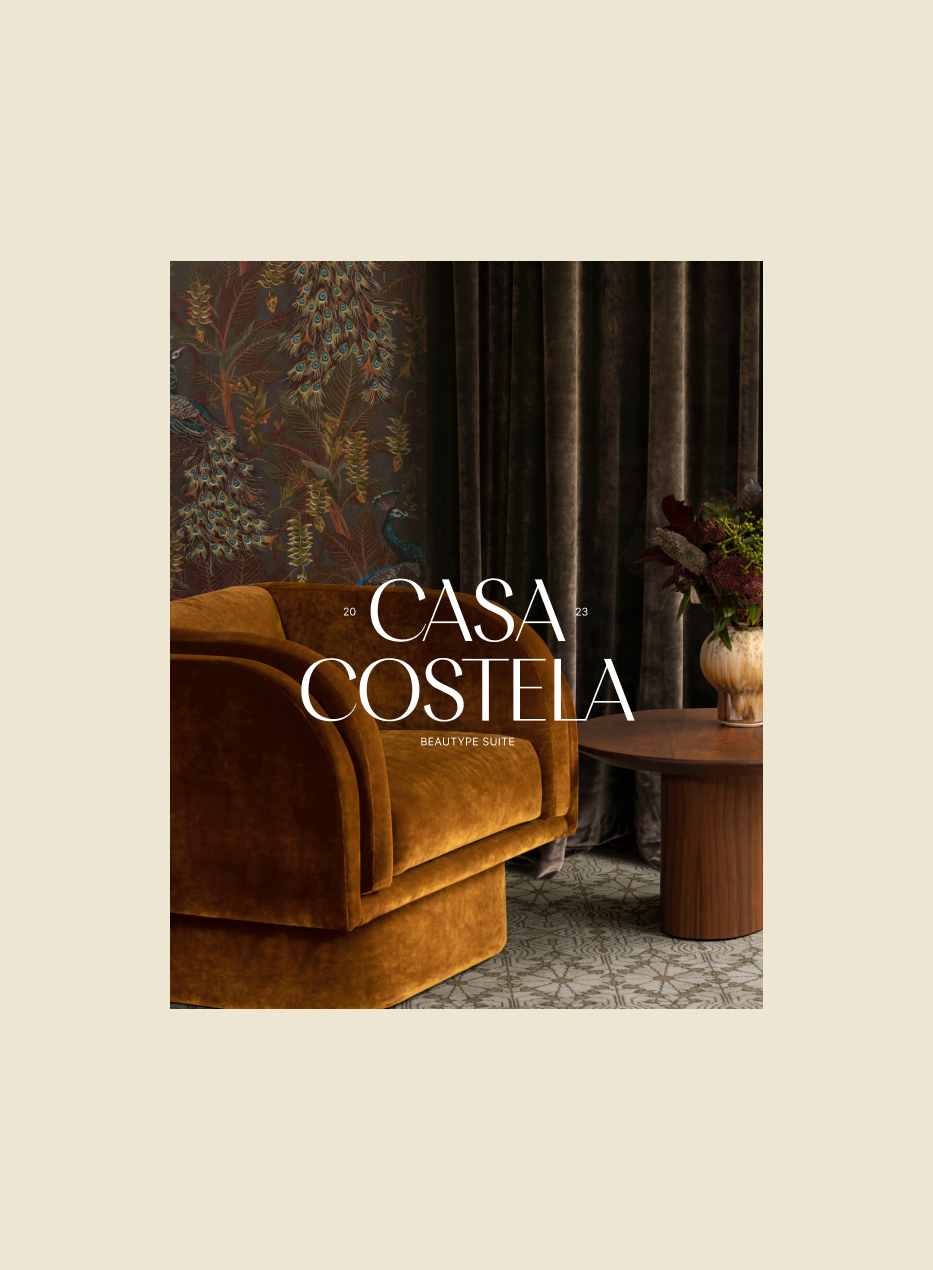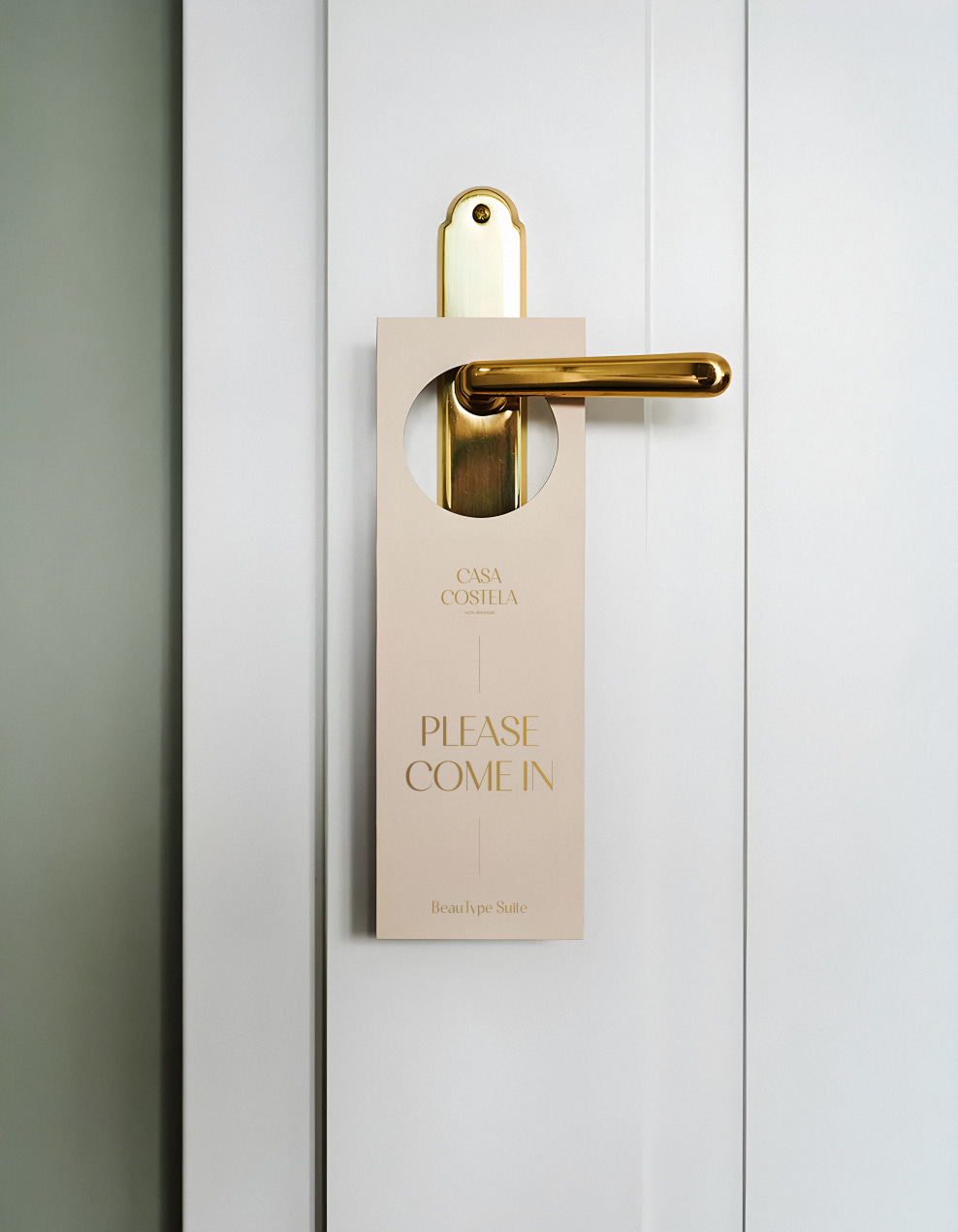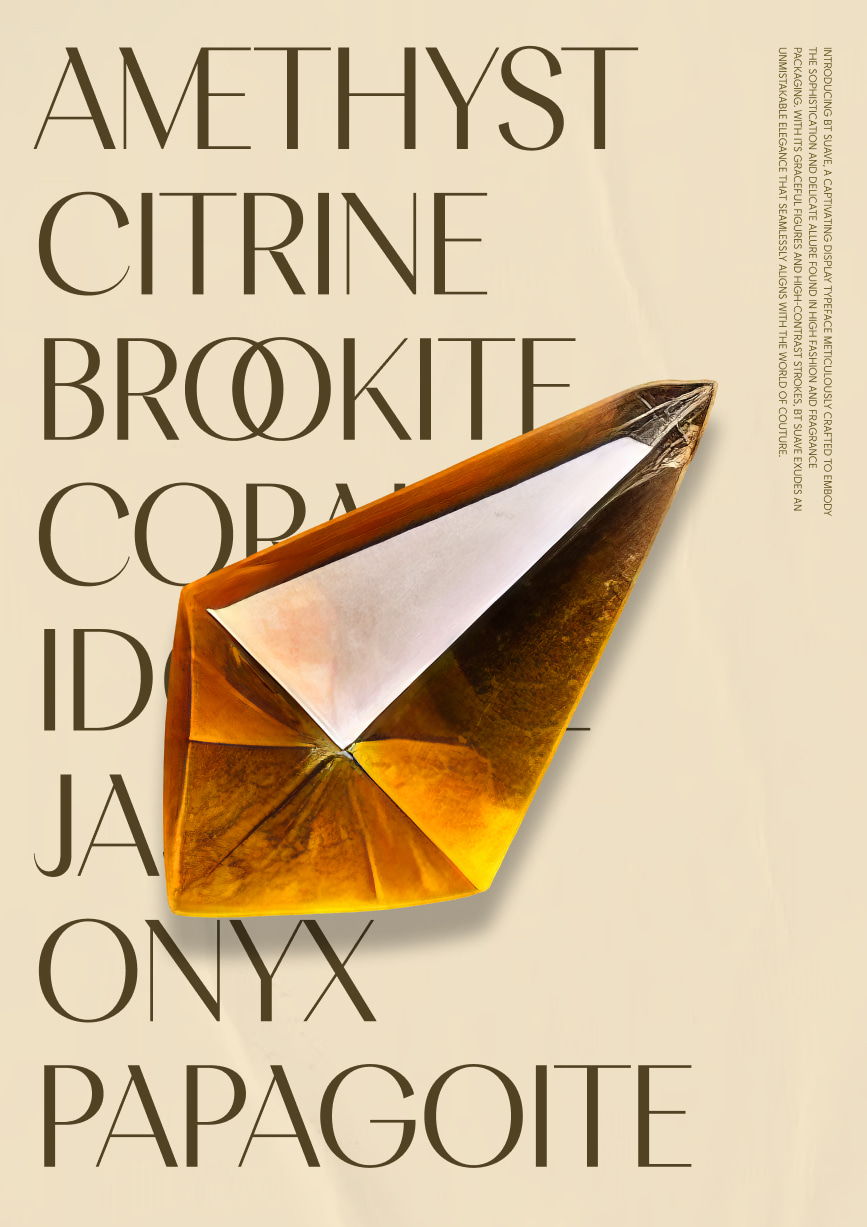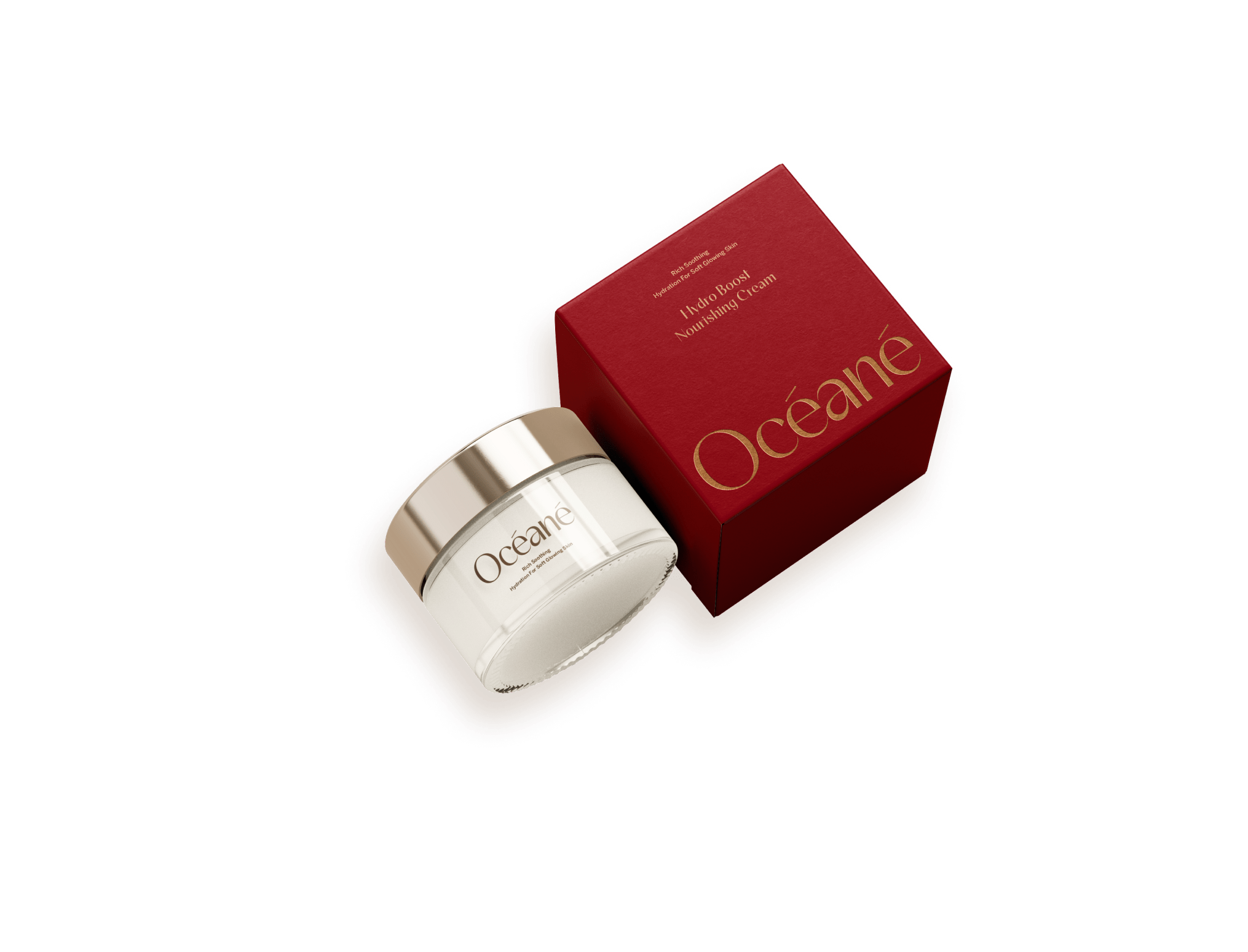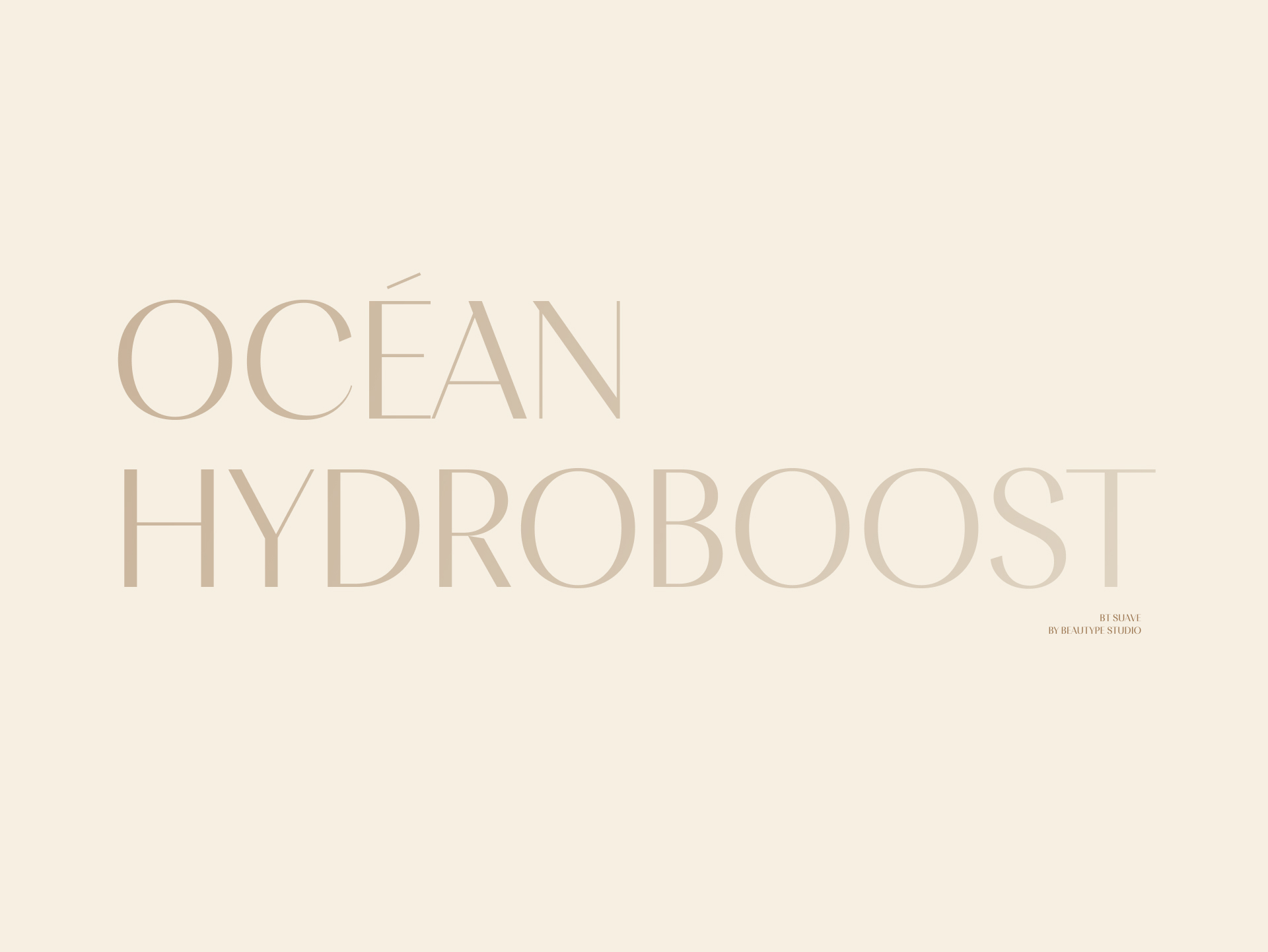
S U A V E
Beautype Studio
Presents
Sculpting Elegance in Letters
display
figures
10 weights
44 ligatures
BT Suave là một bộ chữ display độc đáo được tạo ra với mục đích tạo ra cảm giác nhẹ nhàng, tinh tế và uyển chuyển khi dùng trong thiết kế. Với form dáng hiện đại, đường nét tương phản cao, được chăm chút tỉ mỉ các tiểu tiết, BT Suave này là mảnh ghép hoàn hảo cho các nhãn hiệu thời trang, mỹ phẩm cũng như các thương hiệu khác có chung định hướng visual với bộ chữ. Với 20 styles khác nhau về độ dày và độ nghiêng, BT Suave tự tin hoạt động tốt trong nhiều môi trường, đáp ứng nhu cầu phân cấp phức tạp khi đưa vào ứng dụng.
Kết cấu đặc trưng
BT Suave đặc trưng bởi tương phản nét cao, kết cấu vững vàng, hạn chế cắt gọt phần giao dày-mỏng ở các ký tự có nét nghiêng, loe rộng exist stroke để cân bằng visual weight cho các ký tự có đường cong lớn. Bên cạnh đó, bộ symbol tương phản rất thấp để làm nền cho nhóm ký tự chữ.
Styles & Weights
Hệ thống style và weight đa dạng, lên tới 10 weight chữ, tạo ra sự linh hoạt trong quá trình sử dụng.
Couture Crafted
in Every
Character
Ngôn ngữ
Bộ chữ Latin-base này hỗ trợ đầy đủ các ký tự có dấu tiếng Việt. Bên cạnh việc các dấu được trau chuốt kỹ càng, những ký tự có dấu chữ lệch như ư-ơ-Ư-Ơ được điều chỉnh side-bearing và kerning tỉ mỉ đảm bảo khoảng cách hài hòa với các ký tự khác trong văn bản.
Ligatures & Alternates
Bên cạnh các ký tự thông dụng, chúng tôi cũng xây dựng thêm các ligrature để tối ưu spacing . Ligature sẽ đảm bảo khả năng hiện thị tốt hơn thay cho việc dùng các nhóm ký tự đơn, khiến cho các nhóm ký tự có sự kết nối chặt chẽ. Ngoài ra ligature cũng làm giảm thiểu tối đa sự va chạm nét khi giảm kerning.
Uppercase Ligature
lowercase Ligature
Character Set
Basic Latin
Vietnamese
Ligatures and alternates